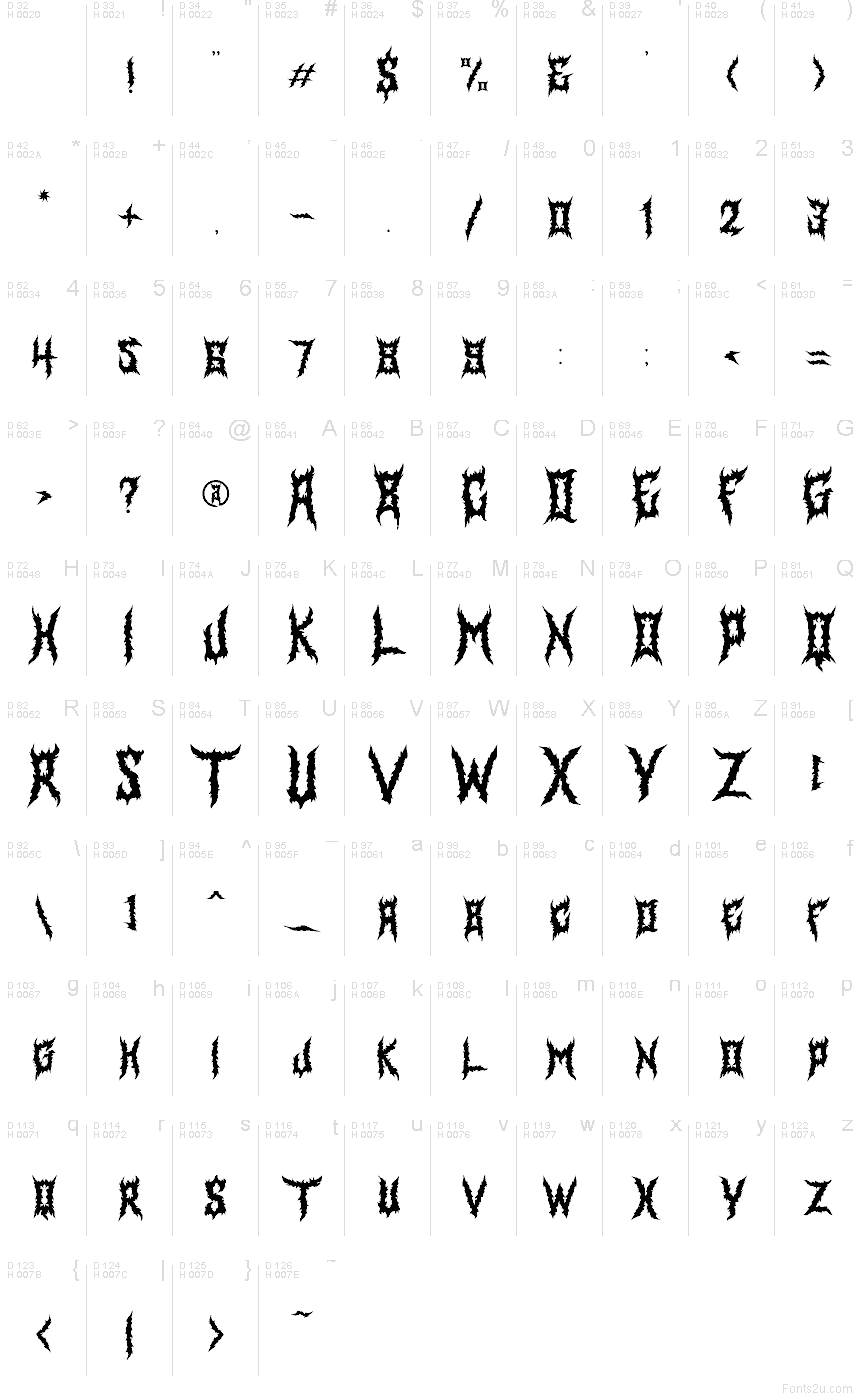
Nekros
Nekros od Putracetol Studio je bezplatné, desivé písmo typu display, v ktorom sa v každom znaku nachádzajú zubaté, plameňovité výrezy. Tvary pôsobia roztrhane a nerovnomerne, s ostrými hrotmi a nepravidelnými okrajmi, ktoré dodávajú abecede drsný, hororový vzhľad.
Nekros výborne funguje na plagátoch na Halloween, obaloch metalových kapiel, grafike pre hry, hororových logách, letákoch na podujatia a temných grafikách na sociálne siete, pretože jeho rozbité obrysy nesú znepokojivý, agresívny rytmus. Toto bezplatné písmo sa hodí aj na krátke nadpisy, varovnú grafiku a strašidelný branding, ak chcete, aby text sám o sebe vyzeral roztrieštene a nepriateľsky.